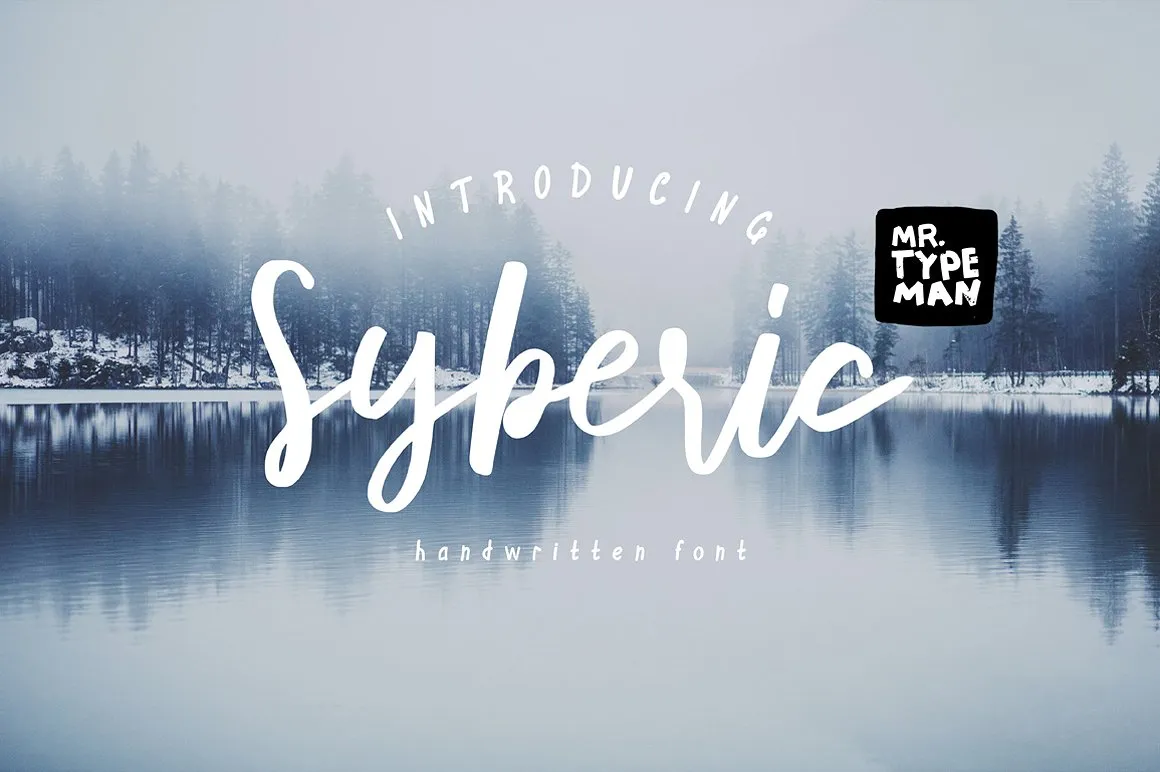
A fonte Syberic Script Font é uma escolha perfeita para designers que procuram alegria no trabalho diário. Crie designs amigáveis e agradáveis com a mão, sem qualquer esforço ou ajuste adicional. Trata-se de uma fonte handwritten naturalmente fluida, ideal tanto para uso cotidiano quanto para os próximos projetos em que você esteja trabalhando. Com letras maiúsculas, minúsculas, pontuação padrão e números inclusos, Syberic também apresenta as letras especiais necessárias para a maioria dos idiomas europeus. É uma opção sólida para qualquer projeto de design em que você esteja trabalhando, seja para criar um site amigável aos usuários, adicionar texto gráfico ao seu produto ou até mesmo imprimir cartões de aniversário personalizados.